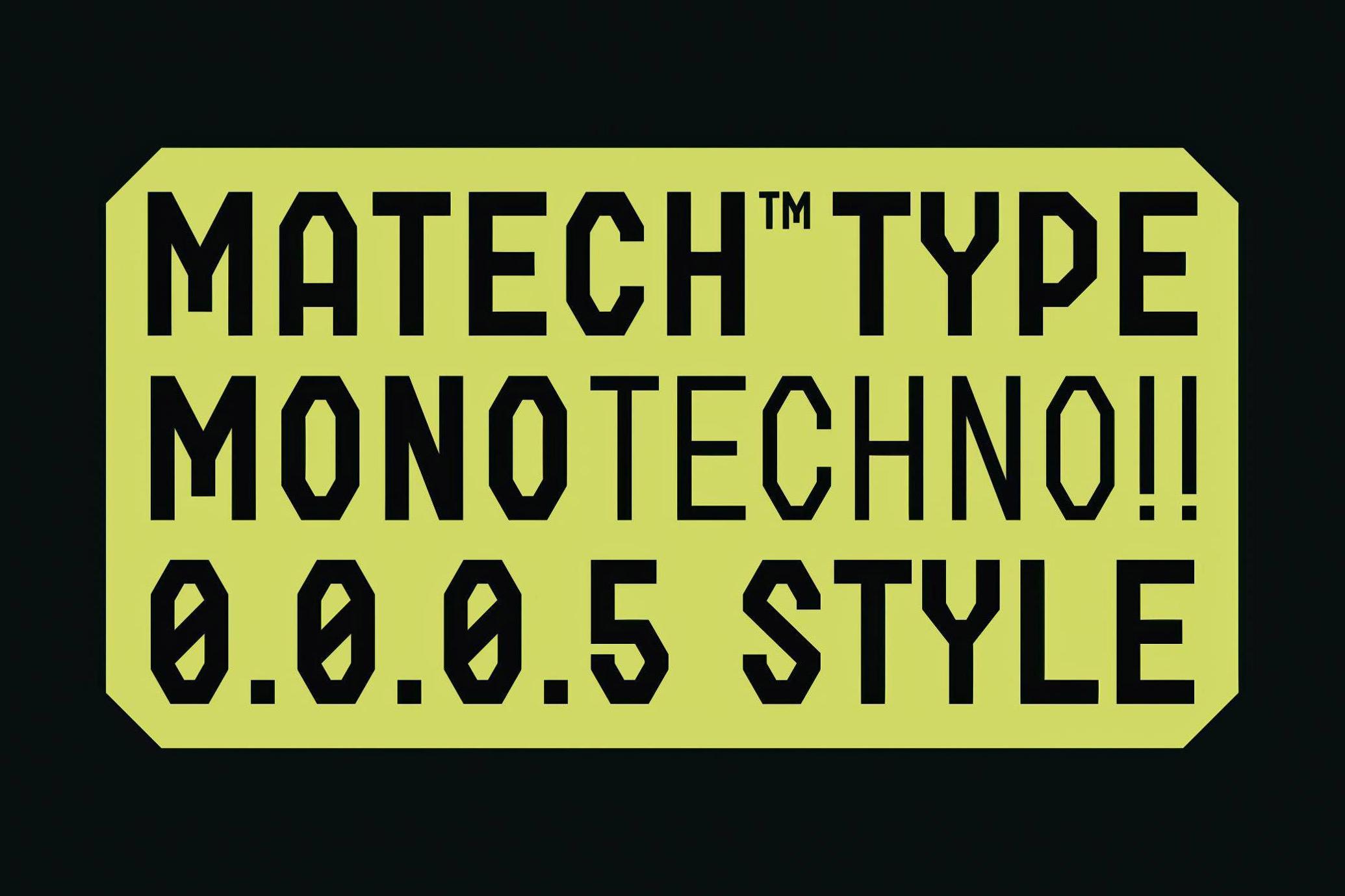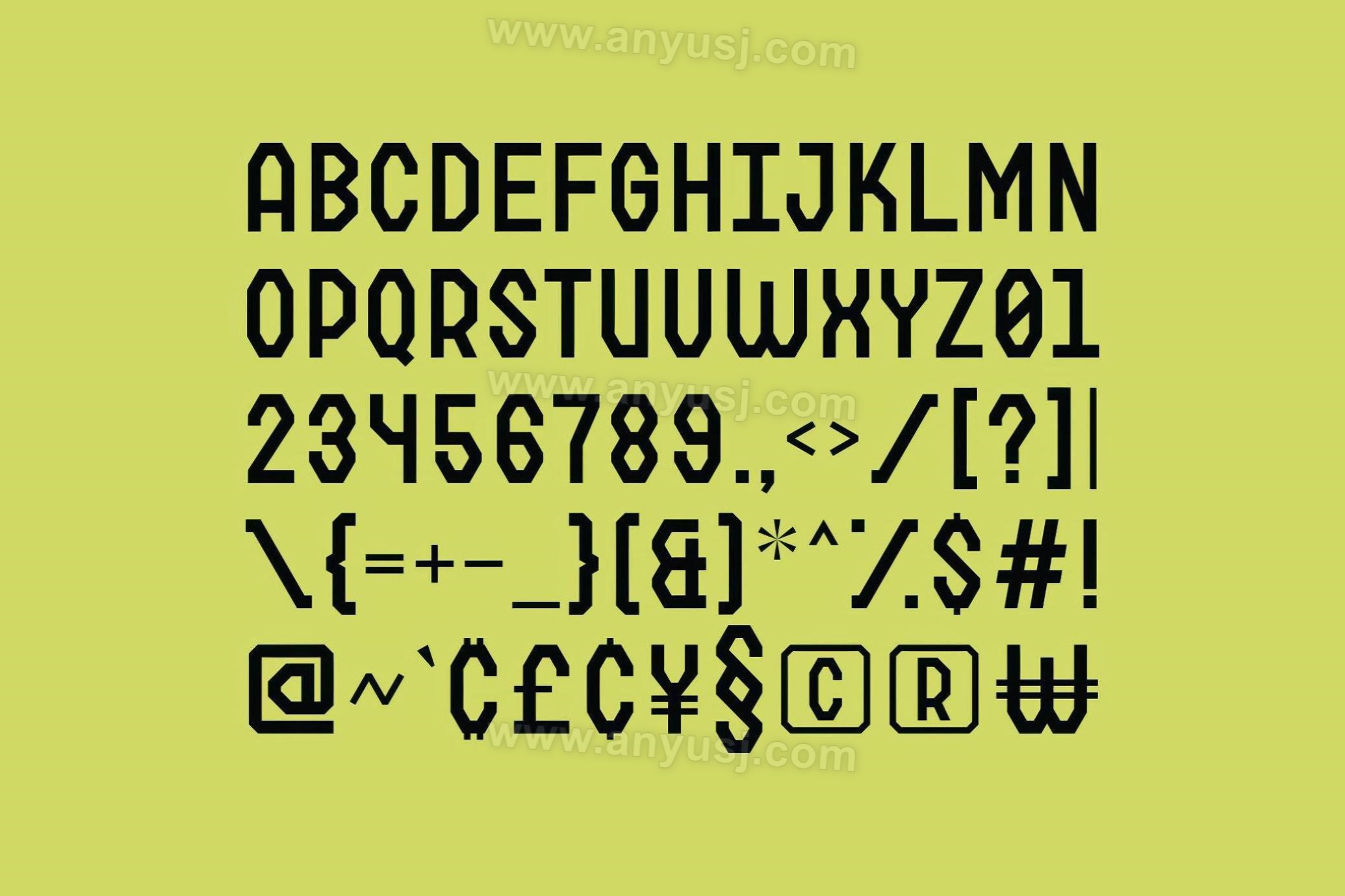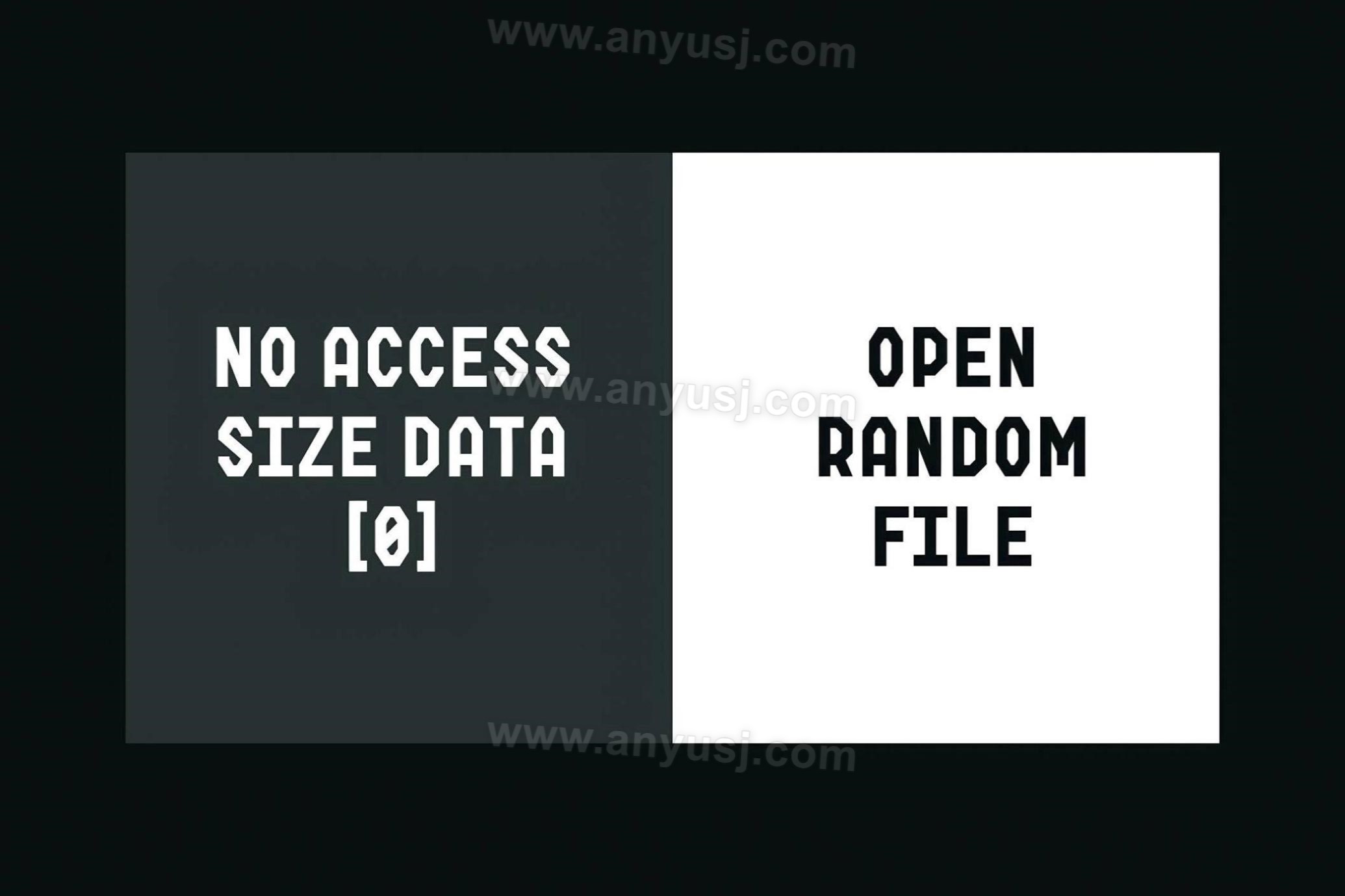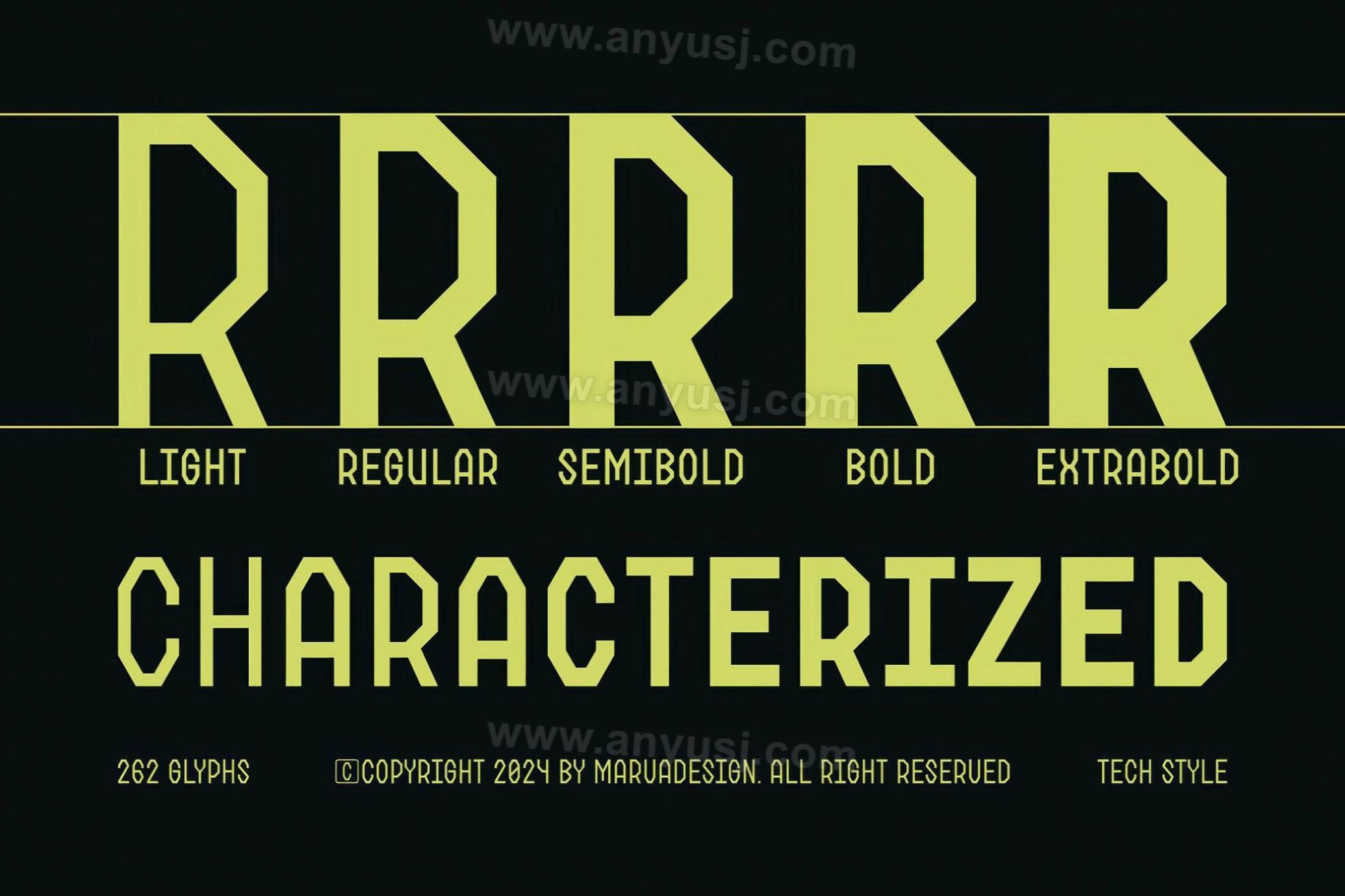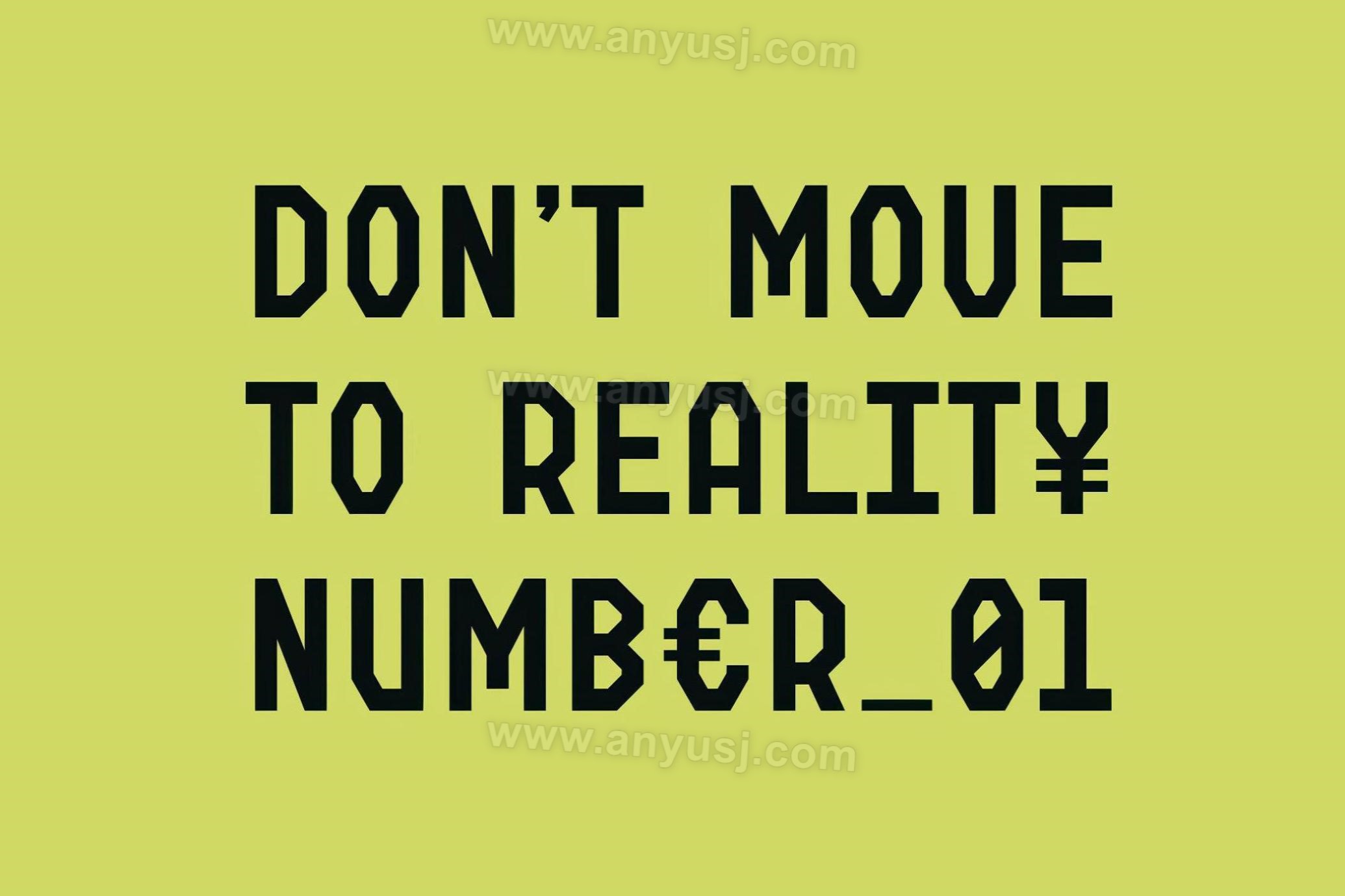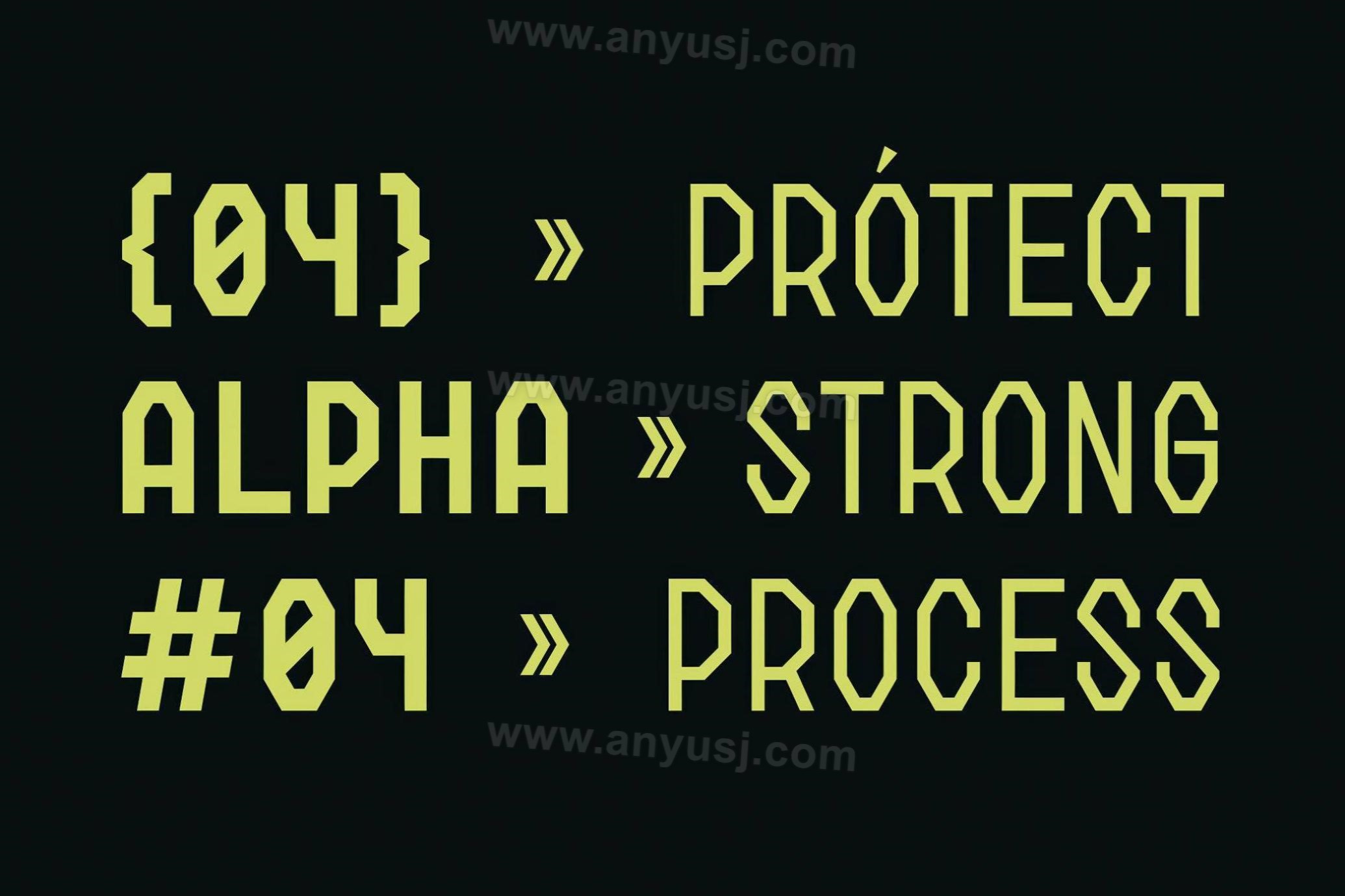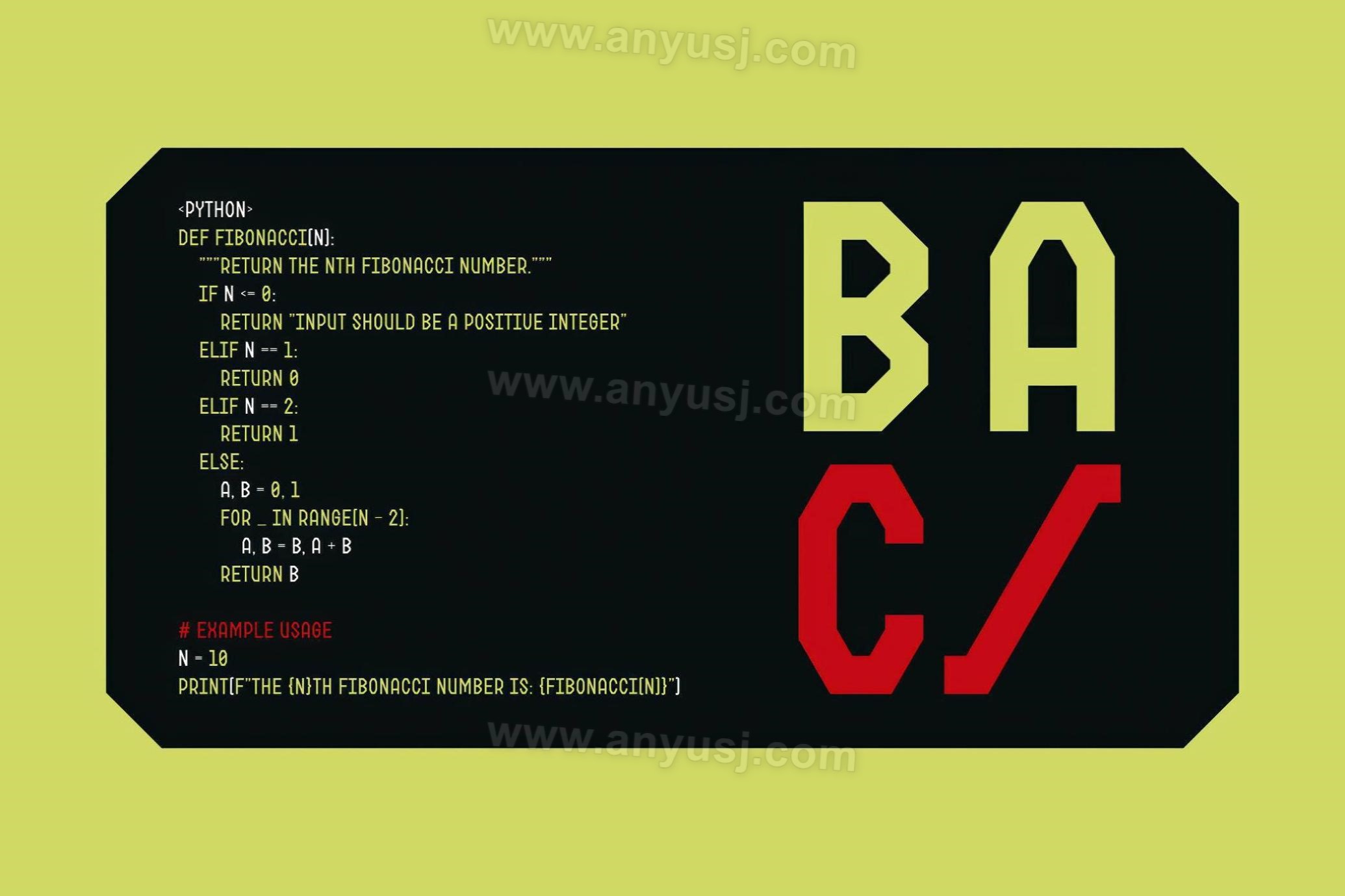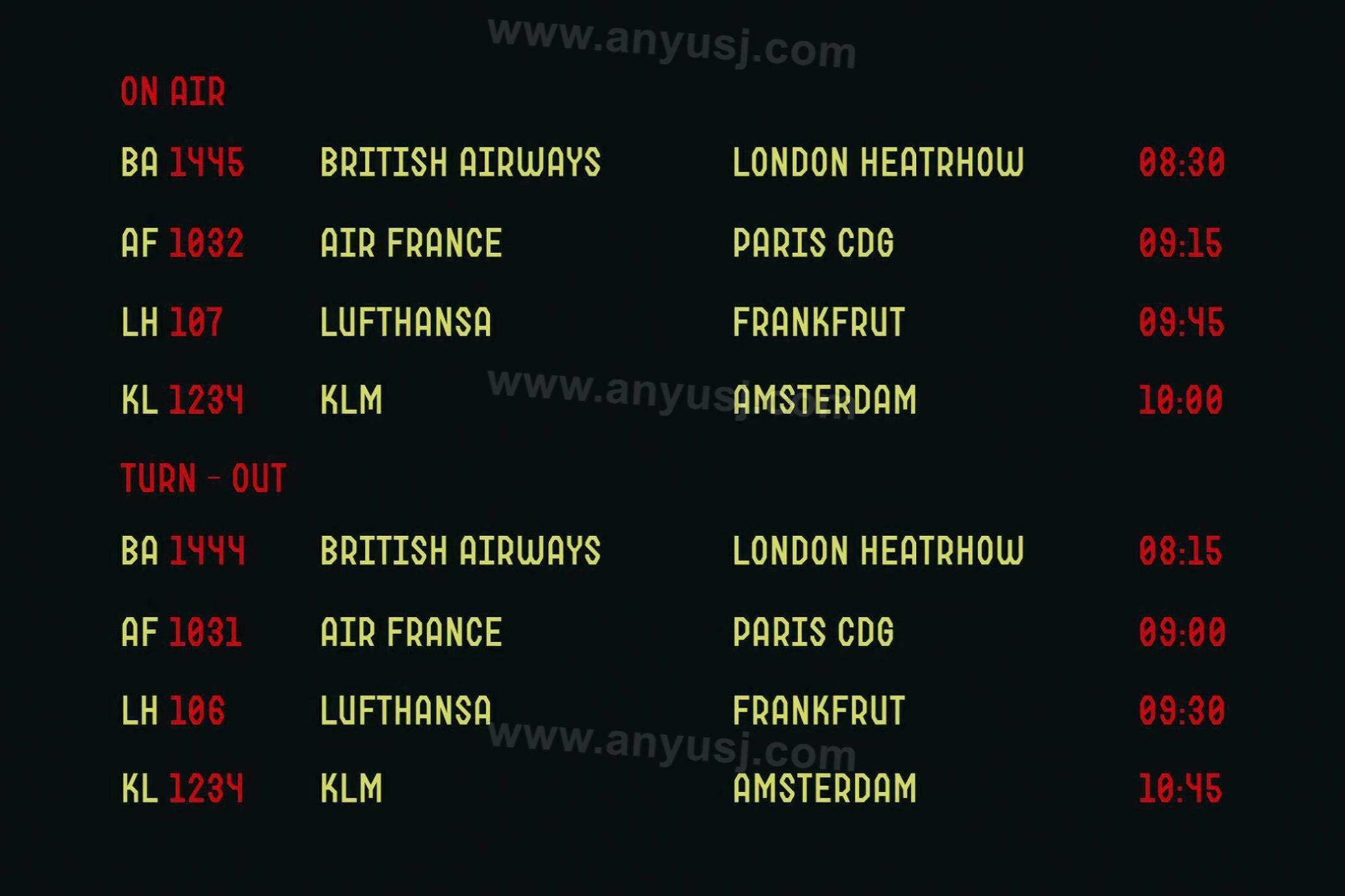
5款复古模块化打印机机械科技游戏标题logo排版无衬线英文字体家族Matech Monospace Techno Font
Matech 字体就像一台机器:它精确、锐利,并专注于实现尽可能高的性能。每个角色都经过精心剪裁(是的,这是正确的词),提供时尚的模块化外观,无缝融入科技、游戏和数字设计领域。包括标点符号、数字和多语言支持 – 因为未来没有国界。从 Light 到 ExtraBold,5 种粗细中的每一种都有一个用途。编码、品牌化或直接从赛博朋克梦想中制作界面 – Matech 带来您所需的结构和强度。